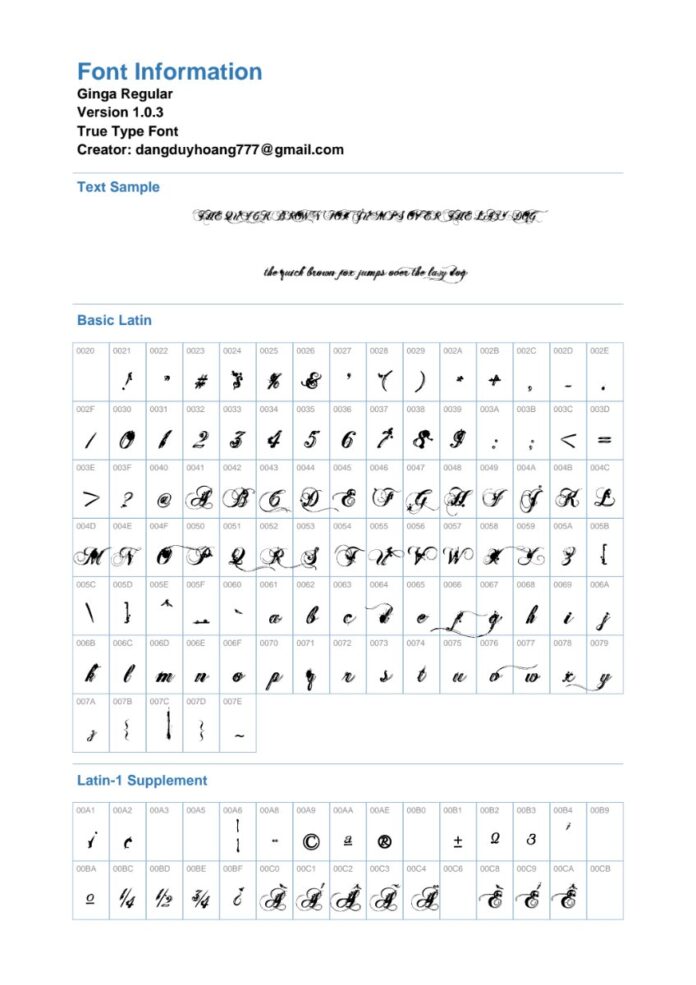
Font UVF Ginga – Chữ viết tay độc đáo. Khám phá Font UVF Ginga, một kiểu chữ viết tay độc đáo và tinh tế, lý tưởng cho các thiết kế cần sự mềm mại, cá tính. Tải ngay để tạo điểm nhấn ấn tượng cho dự án của bạn.
Trong thế giới thiết kế đồ họa đầy sáng tạo, việc lựa chọn font chữ phù hợp đóng vai trò then chốt trong việc truyền tải thông điệp và tạo ấn tượng thị giác. Font UVF Ginga là một trong những lựa chọn tuyệt vời dành cho những ai tìm kiếm sự độc đáo, mềm mại và cá tính trong từng nét chữ. Với phong cách viết tay uyển chuyển, Ginga mang đến vẻ đẹp tinh tế và cảm xúc, phù hợp với nhiều loại hình dự án khác nhau.
Giới thiệu về Font UVF Ginga
Font UVF Ginga, được phát triển bởi tác giả dangduyhoang777, là một kiểu chữ TrueType (TTF) với phiên bản 1.0.3. Đây là một font chữ viết tay (script font) nổi bật với các nét thanh mảnh, bay bổng và có tính nghệ thuật cao. Ginga không chỉ là một font chữ thông thường mà còn là một tác phẩm nghệ thuật, giúp các nhà thiết kế thể hiện sự sáng tạo không giới hạn.
Đặc điểm nổi bật của Font UVF Ginga
- Phong cách viết tay độc đáo: Ginga mô phỏng hoàn hảo nét chữ viết tay tự nhiên, mang lại cảm giác gần gũi và cá nhân hóa cho mọi thiết kế.
- Đa dạng ký tự: Font hỗ trợ đầy đủ các ký tự Latin cơ bản (Basic Latin) và bổ sung (Latin-1 Supplement), bao gồm chữ hoa, chữ thường, số và các ký tự đặc biệt, giúp người dùng linh hoạt trong việc tạo nội dung.
- Tính thẩm mỹ cao: Với các đường nét mềm mại, uyển chuyển, Ginga tạo ra một vẻ đẹp thanh lịch và tinh tế, phù hợp với các thiết kế đòi hỏi sự sang trọng, lãng mạn.
- Dễ dàng ứng dụng: Mặc dù có phong cách nghệ thuật, Ginga vẫn đảm bảo tính dễ đọc, giúp thông điệp được truyền tải rõ ràng mà không làm mất đi vẻ đẹp tổng thể.
Ứng dụng của Font UVF Ginga trong thiết kế
Với những đặc điểm nổi bật, Font UVF Ginga có thể được ứng dụng rộng rãi trong nhiều lĩnh vực thiết kế khác nhau:
Thiết kế thương hiệu và logo
Ginga là lựa chọn lý tưởng cho việc thiết kế logo, bộ nhận diện thương hiệu cho các doanh nghiệp, cửa hàng muốn thể hiện sự độc đáo, tinh tế và mang đậm dấu ấn cá nhân. Đặc biệt phù hợp với các thương hiệu về thời trang, mỹ phẩm, đồ handmade, tiệm bánh, quán cà phê, hoặc các dịch vụ cao cấp.
Thiệp mời và ấn phẩm cá nhân
Khi thiết kế thiệp cưới, thiệp sinh nhật, thiệp chúc mừng hay bất kỳ ấn phẩm cá nhân nào, Ginga sẽ giúp tạo ra một cảm giác ấm áp, lãng mạn và chân thành. Các nét chữ viết tay sẽ làm cho mỗi tấm thiệp trở nên đặc biệt và ý nghĩa hơn.
Thiết kế bao bì sản phẩm
Đối với các sản phẩm thủ công, sản phẩm hữu cơ hoặc các mặt hàng cao cấp, việc sử dụng Font UVF Ginga trên bao bì sẽ tăng thêm giá trị thẩm mỹ, tạo cảm giác sang trọng và độc đáo, thu hút sự chú ý của khách hàng.
Thiết kế website và blog
Trong thiết kế giao diện website hoặc blog, Ginga có thể được dùng cho các tiêu đề, slogan hoặc các đoạn văn bản ngắn cần tạo điểm nhấn. Nó sẽ mang lại một phong cách nhẹ nhàng, thân thiện và nghệ thuật cho trang web của bạn.
Thiết kế poster, banner và quảng cáo
Để tạo ra những poster, banner hoặc ấn phẩm quảng cáo có tính nghệ thuật cao, thu hút ánh nhìn, Ginga là một lựa chọn không thể bỏ qua. Nó giúp thông điệp trở nên mềm mại, dễ chịu hơn, đặc biệt phù hợp với các sự kiện văn hóa, nghệ thuật, hoặc các chương trình khuyến mãi mang tính chất cá nhân.
Để đạt được hiệu quả tốt nhất, bạn nên thử nghiệm Ginga với nhiều kích cỡ và màu sắc khác nhau. Kết hợp Ginga với các font chữ sans-serif hoặc serif đơn giản để tạo sự cân bằng và làm nổi bật vẻ đẹp của nó.